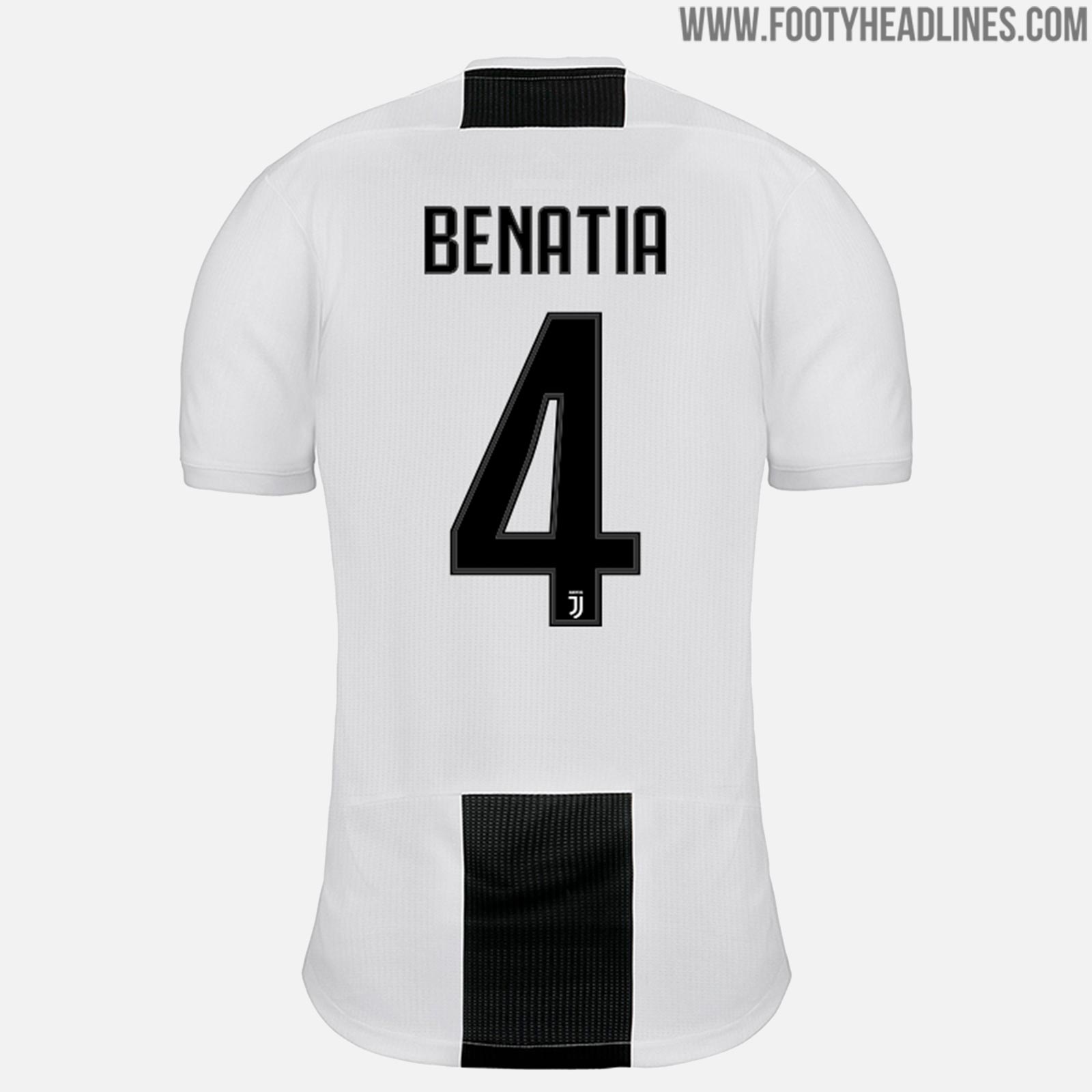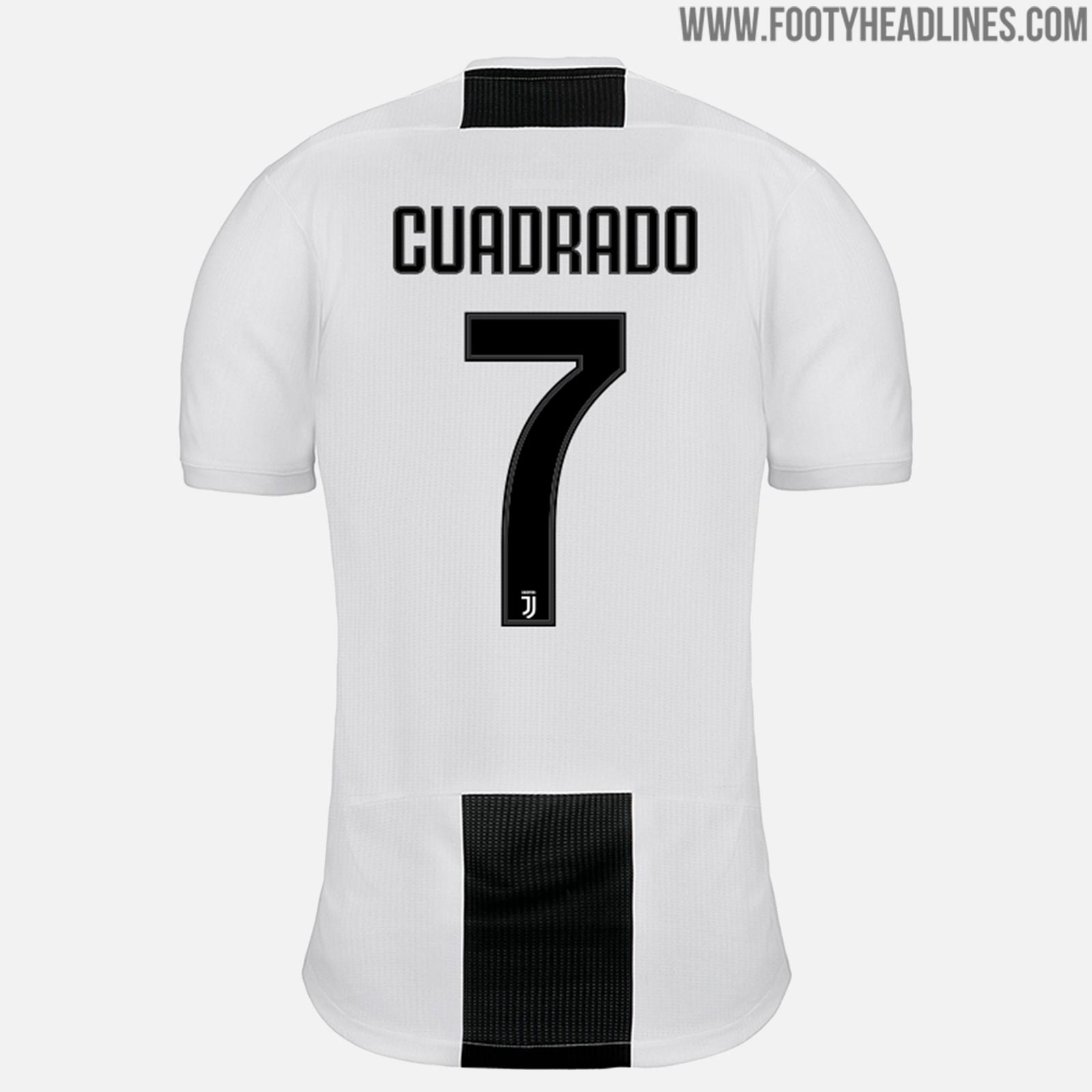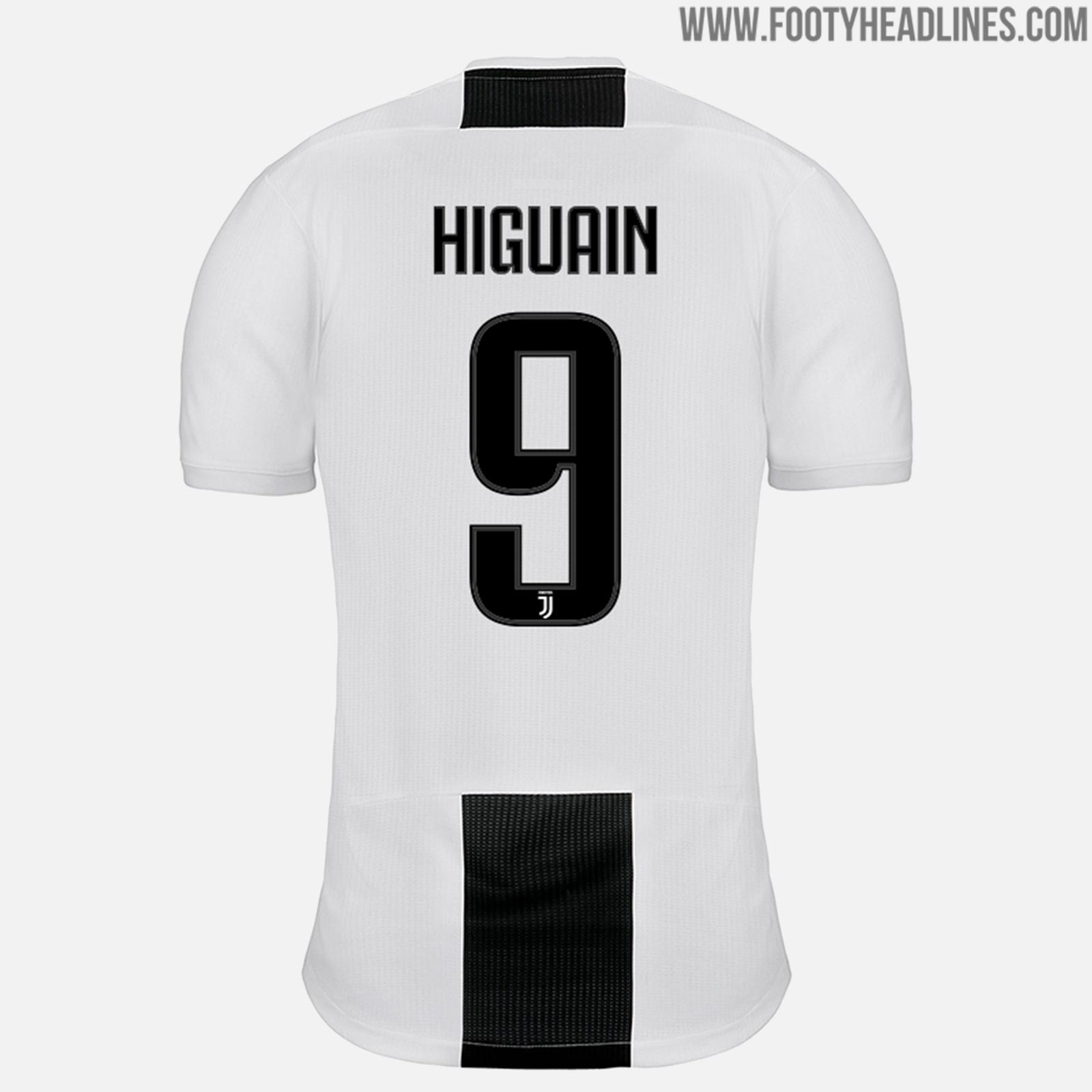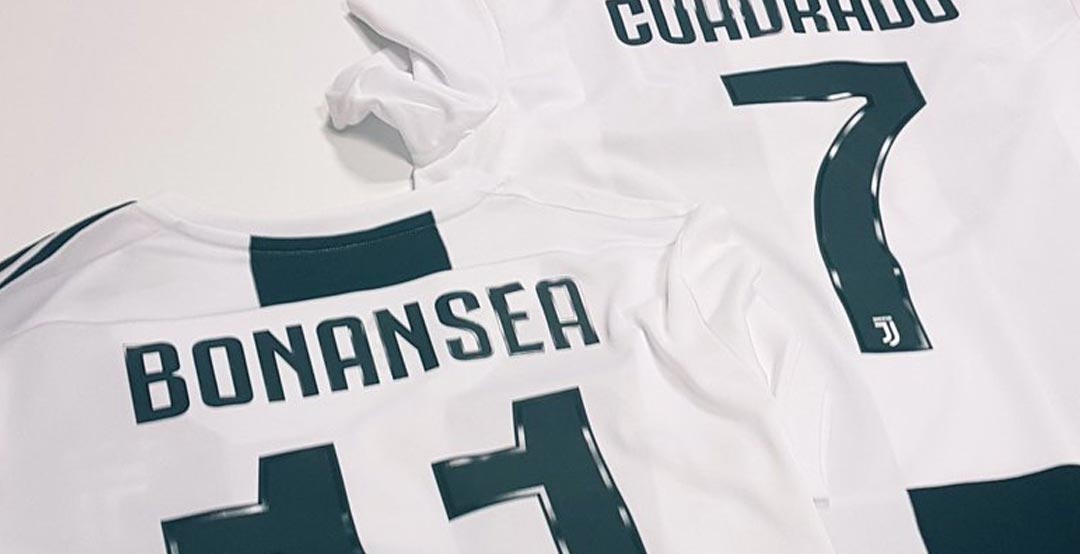
Aktualisiert | Juventus 18-19 Heimtrikot-Schriftart veröffentlicht
Der italienische Gigant Juventus hat diese Woche sein neues Heimtrikot für die Saison 2018-2019 veröffentlicht. Das neue Juventus 2018-19 Trikot weist einen aktualisierten Stil der Namen und Nummern auf.
Adidas Juventus 2018-19 Trikot-Schriftart
Das ist die neue Juventus 2018-19 Trikot-Schriftart.
Die Nummern des neuen Juventus 18-19 Trikots, das den gleichen Schriftartstil wie das 2017-18 Trikot verwendet, setzen auf eine schwarze Hochglanzumrandung, die Klarheit bei Lichteinfall liefert und Nummer und Name der Spieler hervorhebt. Die Umrandung macht die Schriftart auch breiter als die letztjährige.
Juventus wird die 2018-2019 Trikot-Schriftart nächste Saison in allen Wettbewerben verwenden.